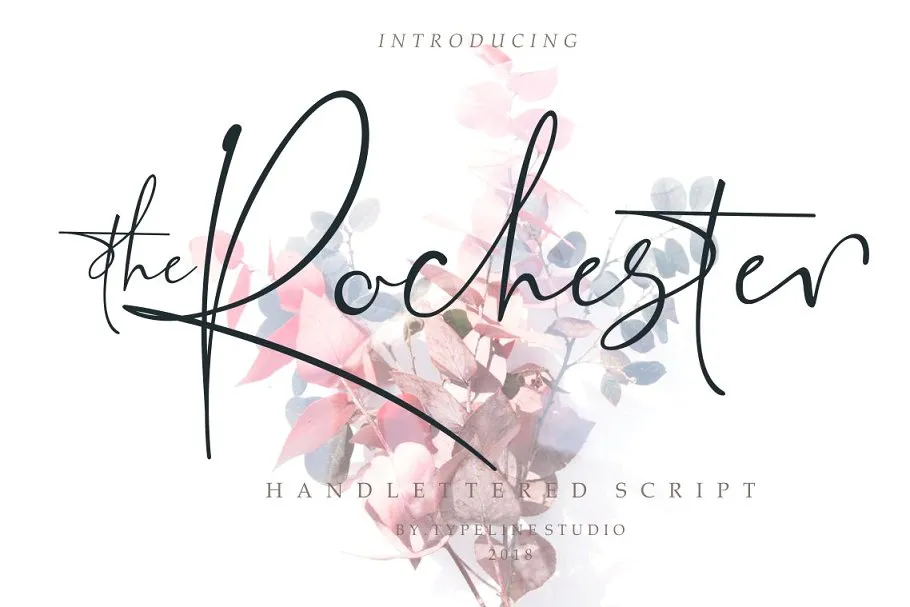
the Rochester Signature Font – Download Grátis
A ‘The Rochester Signature Font’ é uma elegante fonte de script moderna e limpa, inspirada no estilo atual de escrita a mão. Desenvolvida pelo typeline studio para designers como você, esta fonte traz um toque moderno sem perder o sabor genuíno dos traços humanos da escrita a mão. O Rochester é uma cidade que inspirou este design único e versátil. Para o graphic designer, essa fonte é mais do que apenas uma peça de logomarca – ela representa uma ideia perfeita: criar um toque pessoal em qualquer palavra ou frase, tornando-a única e autêntica. O Rochester Signature Font é ideal para designers que procuram dar um toque aconchegante aos seus logos ou marcas, sem perder a essência da letra de mão. Seja você um criador de logomarcas, designer web ou simplesmente um amante dos recursos gráficos, este fonte é perfeita para enriquecer seu trabalho e torná-lo ainda mais pessoal e único.